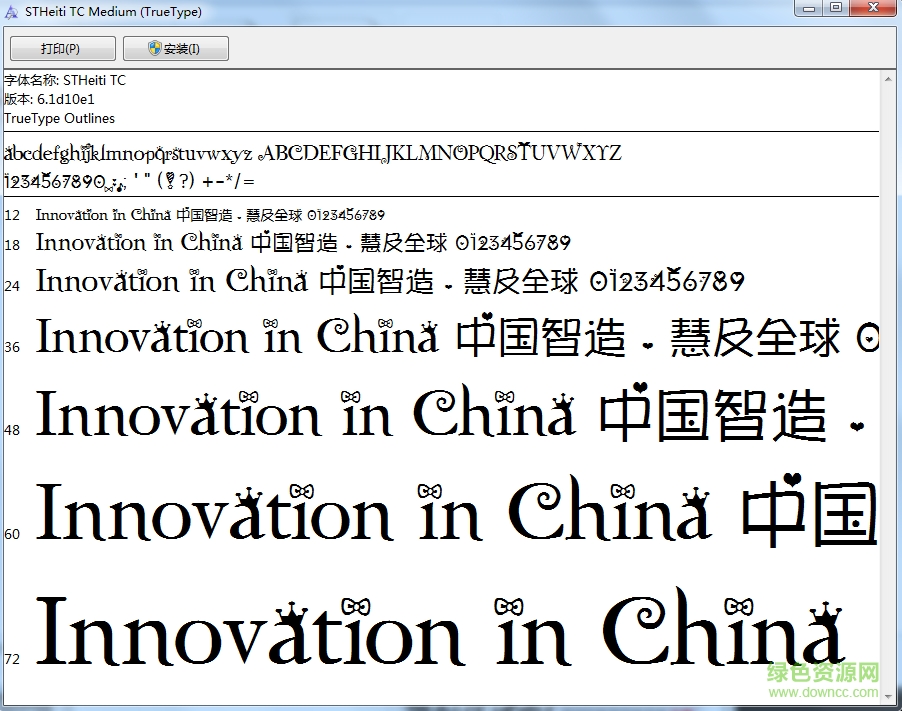
夏日香氣字體ttf
夏日香氣字體是一款清新活潑的現(xiàn)代藝術(shù)字體,可愛的符號和點綴讓你的文字暗生芳香,如夏天般清爽可愛起來,喜歡的朋友歡迎來綠色資源網(wǎng)下載哦!
夏日香氣字體簡介
夏日香氣字體是一款用于植物設(shè)計方面的字體,本作品可用于廣告設(shè)計字體、網(wǎng)頁設(shè)計字體、包裝設(shè)計字體、 屏幕顯示字體等。